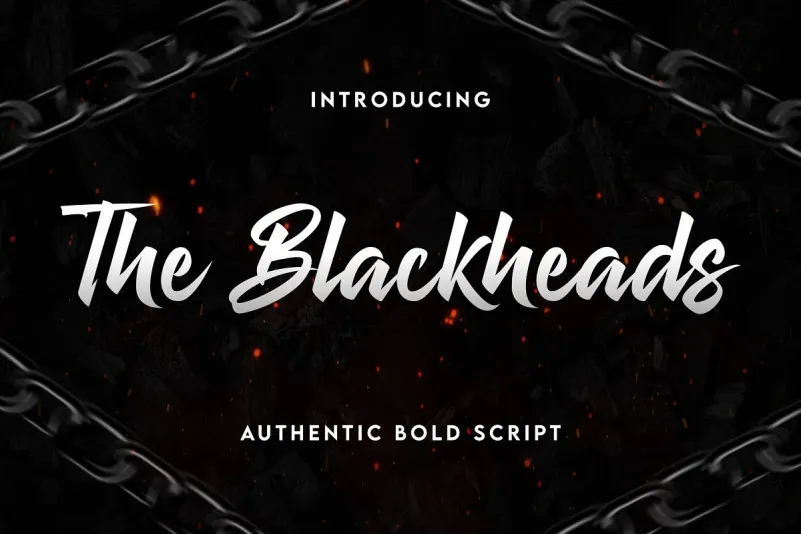
The Blackheads Font
A fonte “The Blackheads” é uma elegante tipografia escrita a mão, projetada por Almarkha Type. Ela se destaca pela sua forma bem definida e redonda, criando um design esplêndido que combina com qualquer projeto visual. Suas letras distintas são perfeitas para diversos usos criativos, incluindo logotipos, cartões de visita, etiquetas, embalagens de produtos, materiais de decoração e até mesmo roupas personalizadas. Sua aparência limpa e a movimentação dramática fazem dela uma escolha perfeita para seu próximo projeto. Seja ele uma identidade visual, uma campanha publicitária ou qualquer outro tipo de trabalho gráfico que precise ser único e impecável, “The Blackheads” se adapta com facilidade e oferece o brilho necessário para tornar sua arte ainda mais impactante.